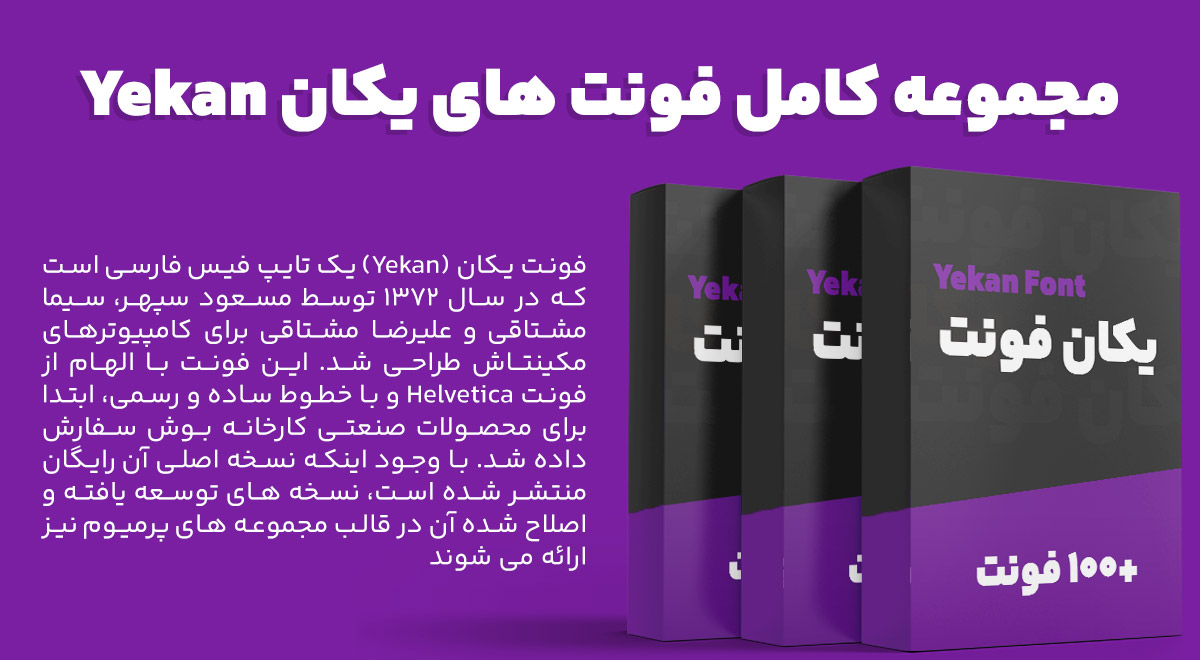
مجموعه فونت یکان فارسی Yekan (+100 فونت)
فونت یکان (Yekan) یک تایپ فیس فارسی است که در سال ۱۳۷۲ توسط مسعود سپهر، سیما مشتاقی و علیرضا مشتاقی برای کامپیوترهای مکینتاش طراحی شد. این فونت با الهام از فونت Helvetica و با خطوط ساده و رسمی، ابتدا برای محصولات صنعتی کارخانه بوش سفارش داده شد. با وجود اینکه نسخه اصلی آن رایگان منتشر شده است، نسخه های توسعه یافته و اصلاح شده آن در قالب مجموعه های پرمیوم نیز ارائه می شوند. فونت یکان به دلیل زیبایی، سادگی و خوانایی بالا، به یکی از پرکاربردترین فونت ها در طراحی های گرافیکی، نشر، وبسایت ها (مانند دیجی کالا و اسنپ) و حتی اسناد رسمی (مانند کارت ملی) تبدیل شده است. این مجموعه شامل +100 فونت با فرمت های TTF, OTF, WOFF, WOFF2, EOT, SVG است.
فونت یکان (Yekan) یکی از مهم ترین و محبوب ترین فونت های فارسی است که نقش بسزایی در ارتقاء تایپ فارسی در محیط دیجیتال داشته است. این فونت در سال ۱۳۷۲ (۱۹۹۳ میلادی) توسط تیم طراحی مسعود سپهر (مدیر پروژه و طراح کلیدهای اصلی)، سیما مشتاقی (طراحی اجزا و مجری یک به یک حروف) و علیرضا مشتاقی (مسئول کارهای فنی) در دفتر طراحی سپهر پارتنرشیپ، ابتدا برای کامپیوترهای مکینتاش طراحی شد.
تاریخچه و فلسفه طراحی:
- الهام از Helvetica: فونت یکان با الهام از فونت معروف و پرکاربرد Helvetica طراحی شده است و به دنبال ایجاد یک قلم فارسی با خطوط ساده و رسمی بود که پیش از آن در فونت های فارسی رایج نبود.
- پروژه اولیه: طراحی این فونت در ابتدا به سفارش کارخانه بوش برای لوگوتایپ فارسی محصولات صنعتی این شرکت آغاز شد.
- انتشار عمومی: پس از آن، برای استفاده کاربران مکینتاش در ایران منتشر گردید. با ورود کامپیوترهای شخصی و نیاز به حروف فارسی، فونت یکان بدون هماهنگی با طراح، برای سیستم عامل های ویندوز و لینوکس نیز جنریت شد و در دسترس همگان قرار گرفت.
ویژگی های فونت یکان:
- زیبایی، شکیل و حرفه ای: با وجود سادگی، یکان جلوه ای زیبا، شکیل و حرفه ای به محصولات گرافیک فارسی می بخشد. این فونت در طراحی لوگوها، برندها، نشریات، سازمان ها و وبسایت های معروفی مانند لوگوی بوش، سامسونگ، شبکه من و تو، دیجی کالا، اسنپ و حتی بر روی کارت ملی مورد استفاده قرار گرفته است.
- خوانایی بالا: فونت یکان دارای حروف کامل و صحیح فارسی، علائم نگارشی، اعداد، نمادها و آیکون های مختلف است. این فونت با تمام برنامه های گرافیکی و ویرایشگرهای متن سازگار بوده و مشکلات کمی در نمایش حروف دارد. همچنین برای صفحات ریسپانسیو وب و نمایش در رزولوشن ها و دستگاه های مختلف بسیار مناسب است.
- گسترش و نسخه های متنوع: با گذر زمان، نسخه های متعددی از فونت یکان توسط طراحان مختلف توسعه و اصلاح شده اند. این نسخه ها شامل وزن ها و سبک های متنوعی هستند که برای نیازهای خاص در طراحی (مانند وب، موبایل، و چاپ) بهینه شده اند.
فونت یکان (Yekan) به دلیل ویژگی های برجسته خود، در طیف گسترده ای از کاربردها در حوزه های طراحی گرافیک، نشر، وب، و اپلیکیشن های موبایل مورد استفاده قرار می گیرد.
کاربردهای اصلی:
- طراحی لوگو و برندسازی: ظاهر ساده و حرفه ای یکان، آن را به گزینه ای عالی برای طراحی لوگوهای شرکت ها و برندها تبدیل کرده است، مانند لوگوی بوش و سامسونگ که با این فونت طراحی شده اند.
- نشر و چاپ: این فونت در طراحی کتاب، پوستر، مجلات و نشریات کاربرد فراوانی دارد. خوانایی بالای آن باعث می شود که متون چاپی، حتی در حجم بالا، به راحتی قابل خواندن باشند.
- وبسایت ها و اپلیکیشن های موبایل: با توجه به بهینه سازی برای محیط وب و دستگاه های دیجیتال، یکان فونت اصلی بسیاری از وبسایت ها (مانند دیجی کالا) و اپلیکیشن های موبایل (مانند اسنپ) است. نسخه های خاص “Yekan Web” برای این منظور بهینه سازی شده اند.
- اسناد رسمی و اداری: استفاده از یکان در کارت ملی و اسناد رسمی نشان دهنده رسمیت و وضوح بالای این فونت است. همچنین در پایان نامه ها، گزارش ها و مکاتبات اداری کاربرد دارد.
- تبلیغات و بیلبوردها: ظاهر قوی و خوانای یکان، آن را برای استفاده در بیلبوردها و کارهای تبلیغاتی بزرگ نیز مناسب می سازد.
- طراحی رابط کاربری (UI): در طراحی رابط های کاربری نرم افزارها و سیستم های عامل، به دلیل سادگی و وضوح، بسیار مورد توجه قرار گرفته است.